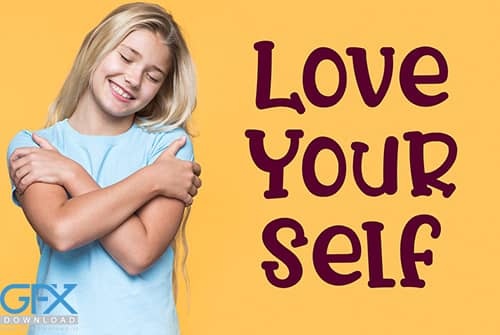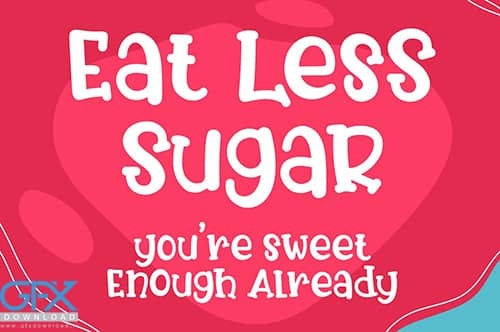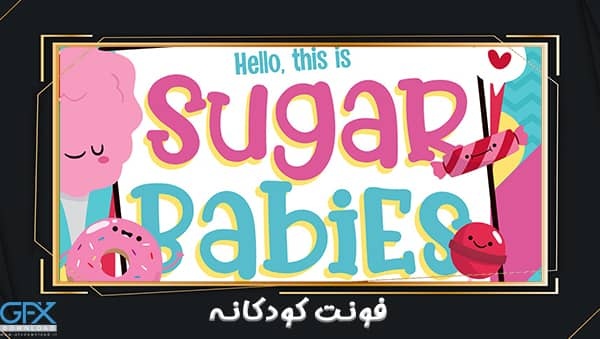
دانلود فونت بچه گانه
فونت انگلیسی بچه گانه و کارتونی
دانلود فونت انگلیسی بچه گانه و کارتونی
شما می توانید در طراحی های مختلف از این فونت زیبا و کودکانه استفاده نمایید. دانلود فونت بچه گانه Sugar Babies به سبک کارتونی و کودکان. استفاده از این فونت طراحی شما را زیبا تر ، زیبا ، سرگرم کننده و رنگارنگ می کند. با فرمت های (OTF ، TTF ، WOFF). شامل مجموعه کاراکتر، اعداد و علائم نگارشی (استاندارد OpenType)، لهجه ها (نویسه های چند زبانه).